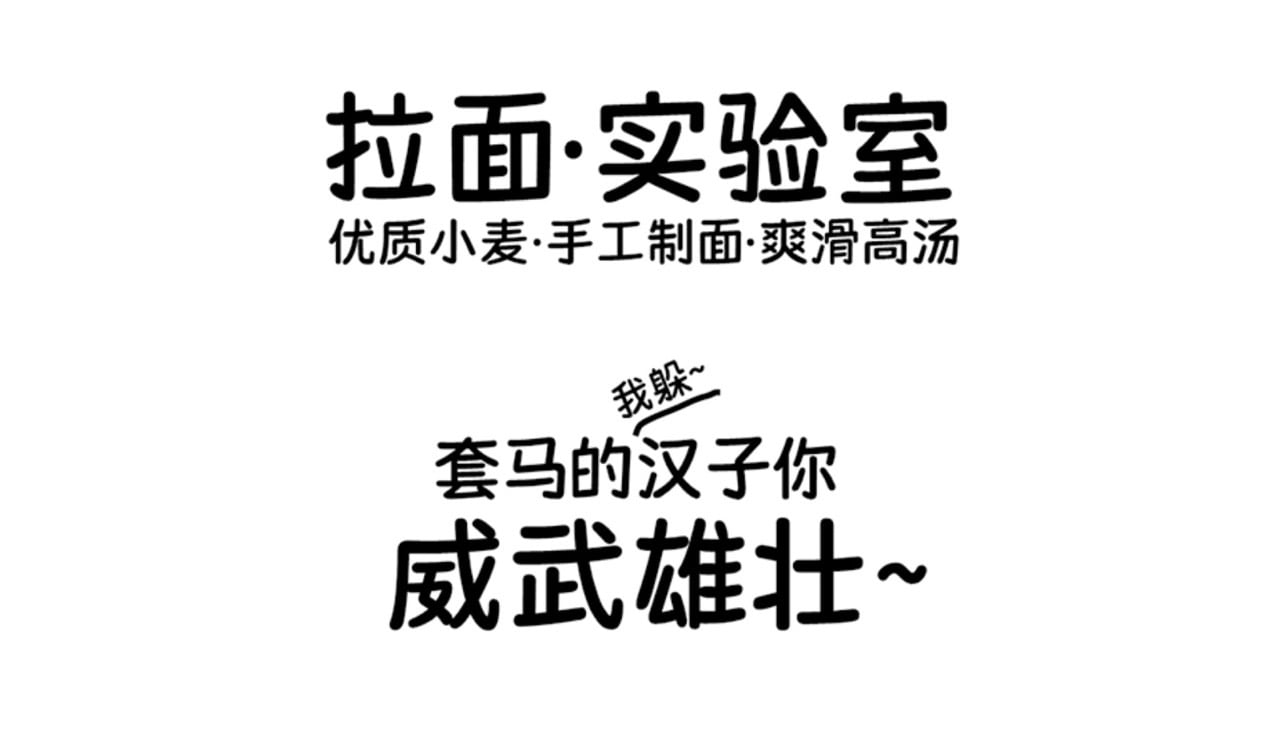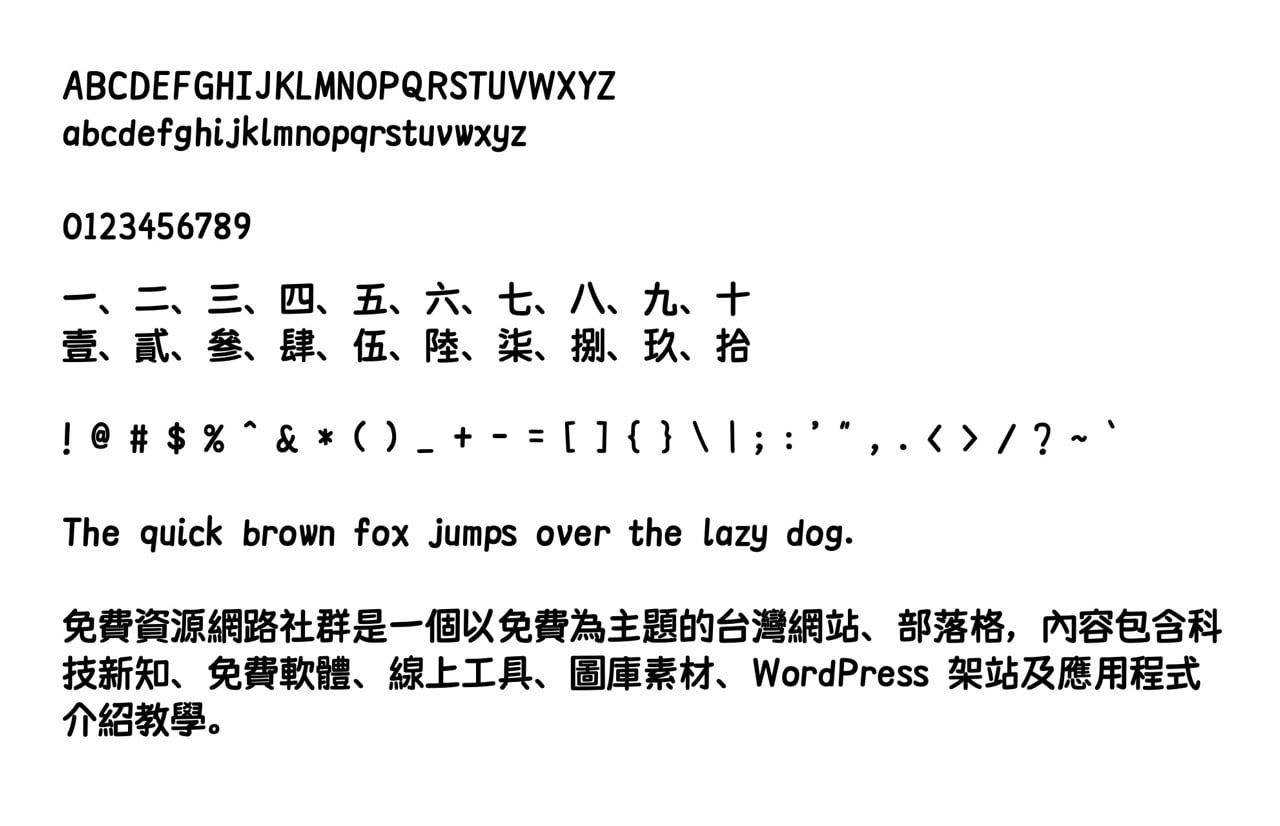
今天要來推薦給大家的是一款俏皮、逗趣的免費字型「荊南麥圓體」,這款字體設計靈感是來自韓國綜藝節目,如果有在看韓綜的話,一定會發現他們常常把一些效果或是笑點以大大的字幕呈現在畫面中,荊南麥圓體使用手寫圓潤的筆畫讓字體看起來很可愛,很適合使用於食品、嬰幼兒或是兒童類型的設計。
荊南麥圓體簡介:源自字庫與開源社群的結晶
字體設計特色
荊南麥圓體採用極具親和力的手寫筆觸,其最大的特色在於均一的線條粗細設計。字體結構清晰,筆畫間刻意保持適度留白,減少細碎的連筆干擾,使整體視覺更加活潑。邊緣處經過圓潤飽滿的導角處理是它的一大特色。
這個字型以簡體中文標準(GB2312)為核心開發,但也包含一定程度的繁體中文支援,例如 Big5(大五碼)常用字支援率約為 75%,大約有近萬個字元;常用國字標準字體表部分已涵蓋大部分台灣日常使用的繁體字,如果不是太複雜或罕見的字應該都不會有缺字問題。
下圖是荊南麥圓體的一些常用字元,包括大小寫英文、數字、中文數字、特殊符號、英文和中文效果,看得出來在這些字元上都能正常顯示,尤其是這類活潑可愛的手寫字其實應用範圍相當廣泛,有興趣的朋友可以自行去下載來試試看。